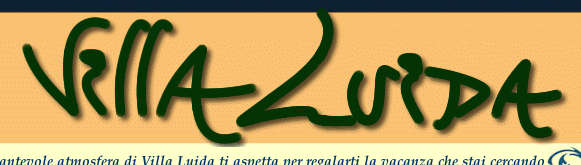
Logofont auf http://www.villaluida.com/
Okay, bei näherer Betrachtung und unter Anwendung ganz strenger Regeln ist das tatsächlich ein grünliches Schwarz... :wink:
Weiterhin hoffe ich sehr, dass sich herausstellt dass das kein Font ist, nicht mal Freeware, sondern handgezeichnet -grusel- ;)